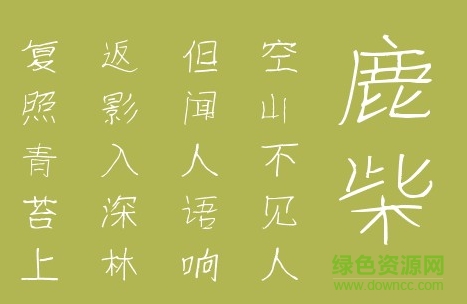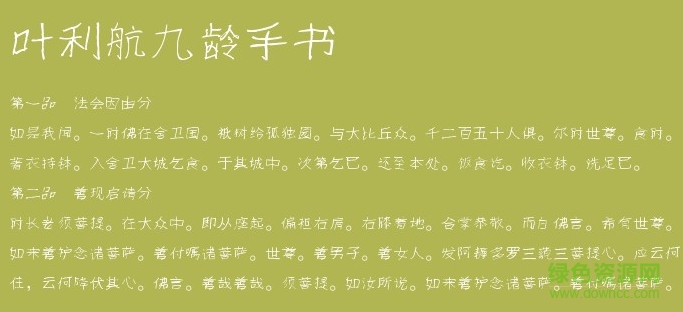
葉利航九齡手書(shū)字體是書(shū)法家之子葉利航的手寫(xiě)字體,這款字體筆畫(huà)線(xiàn)條細(xì)膩,極具卡通風(fēng)格,從字體中可以看出充滿(mǎn)了童趣、純真,喜歡的朋友歡迎來(lái)綠色資源網(wǎng)下載使用!
葉利航是葉根友的兒子,已經(jīng)九歲了,故取名葉利航九齡手書(shū),是一款九歲小孩書(shū)寫(xiě)的字體,這么多年來(lái),一直想出一套真正意義上的小孩子字體,自己也曾刻意的去模仿小孩子的筆法和感覺(jué)去寫(xiě)字體,比如葉根友童體、葉根友小京楷字體等,都是在這種念想中去模仿孩童字體風(fēng)格,但是始終不如意,今年暑假的時(shí)候,跟兒子商量,能不能書(shū)寫(xiě)一套字稿?于是,放棄了他暑假的時(shí)間,終于完成了這字體的書(shū)寫(xiě),當(dāng)然,作為獎(jiǎng)勵(lì),特別帶他去北京旅游。